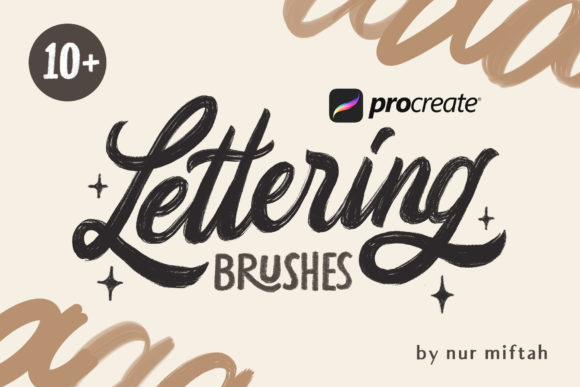
Procreate Lettering Brushes
Trouver les bons éléments de conception peut être un défi, mais Procreate Lettering Brushes propose une collection exceptionnelle qui rehausse instantanément votre travail.